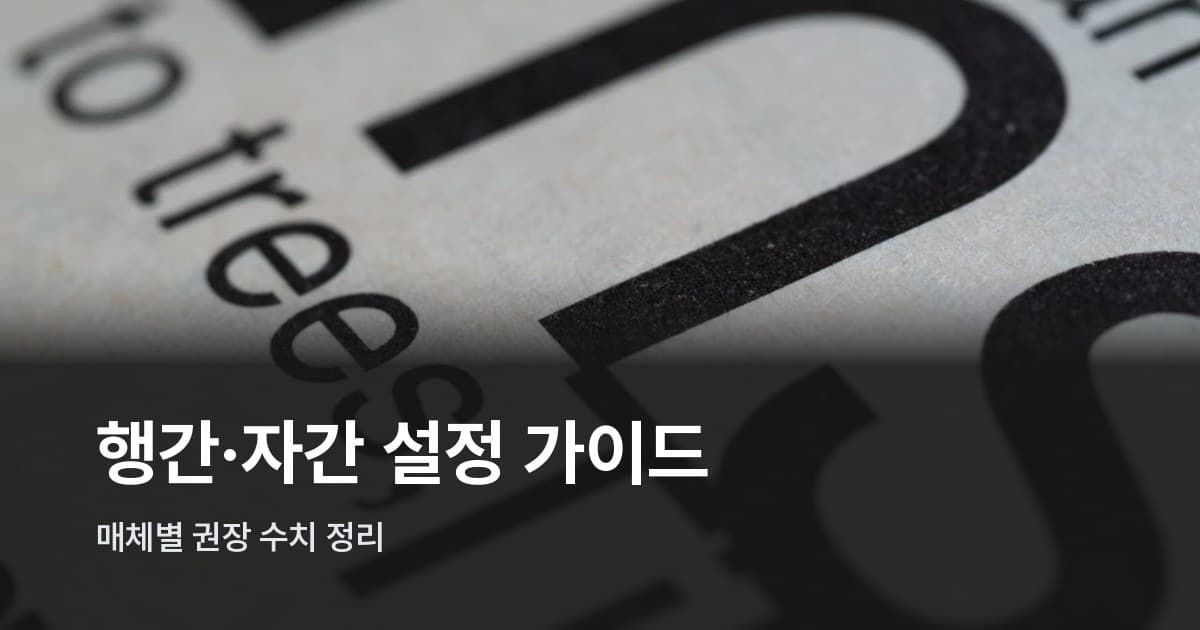
한글 폰트 행간·자간, 역할과 매체별로 수치가 다 다르다
흰 종이에 인쇄된 텍스트 클로즈업
line-height: 1.6을 나눔고딕에 적용했을 때와 Pretendard에 적용했을 때, 결과가 같은가? 눈으로 보면 다르다. 같은 수치를 줬는데 왜 다를까 — 그 질문이 이 글의 출발점이다.
행간과 자간 수치는 역할·매체만큼이나 폰트 자체의 구조에 영향을 받는다. 어느 폰트는 정사각형 틀을 꽉 채우고, 어느 폰트는 획이 가늘고 여백이 남는다. 이 밀도 차이가 동일 수치에서 완전히 다른 시각 밀도를 만든다. 수치 표를 보기 전에 이 원리를 이해하지 않으면, 표를 외워도 새 폰트로 바꿀 때마다 처음부터 다시 시작하게 된다.
폰트 구조가 같은 수치를 다르게 만든다
한글 서체는 대부분 초성·중성·종성이 고정된 정방형(正方形) 틀 안에 조합된다. 1980년대 디지털 조판이 표준화된 이후 이 구조가 굳어졌는데, 이 틀 안에서 획을 얼마나 크게 채우는지가 서체마다 다르다.
획이 틀을 빡빡하게 채우는 서체(나눔고딕, 본고딕 계열)는 글자 자체가 시각적으로 크게 보인다. 같은 font-size: 16px라도 텍스트 덩어리가 더 무겁게 느껴지고, 행간을 조금만 좁혀도 줄이 답답해 보인다. 나눔고딕으로 본문을 잡아두고 line-height: 1.6을 적용해 보면 "조금 빽빽하다"는 인상이 드는데, 1.7이나 1.75로 올리면 훨씬 숨통이 트인다. 긴 글을 읽을 때 특히 차이가 도드라진다.
반면 획이 가늘고 여백을 남기는 서체(Pretendard, Noto Sans KR)는 동일 크기에서 시각적으로 좀 더 작고 가볍게 느껴지며, 행간 1.6과 1.7의 차이가 상대적으로 덜 도드라진다. Pretendard로 블로그 본문을 짜면 1.6에서도 충분히 읽힌다는 느낌을 받는 경우가 많다. KoPub 바탕체 같은 명조 계열은 조금 달라서, 세리프 획의 특성상 행간을 1.7~1.8로 넉넉히 주지 않으면 획 끝부분이 서로 가까워 보여 뭉쳐 보이는 느낌이 난다.
자간도 마찬가지다. 정방형 틀의 모든 글자는 같은 폭을 갖는다 — 영문처럼 글자 쌍별로 커닝(kerning) 값이 다르게 들어가지 않는다. 이 균일한 고정 폭이 기본 상태에서 자간을 시각적으로 넓게 느끼게 만드는 원인이다. 그래서 한글에서 -0.01em 전후의 음수 자간이 관행처럼 쓰인다. 영문 본문에서 자간을 음수로 조정하는 일이 드문 것과 대조적이다.
폰트를 바꿀 때마다 행간·자간을 재확인해야 한다는 게 규칙이지 예외가 아니다. 같은 line-height: 1.6을 줘도 나눔고딕은 답답하고 Pretendard는 여유 있어 보인다면, 수치가 틀린 게 아니라 폰트의 획 밀도가 다른 거다.
한글 자간이 음수여야 하는 구조적 이유
영문 알파벳은 글자마다 폭이 다르고, 폰트 제작 단계에서 글자 쌍별로 커닝 값이 세밀하게 설정된다. 대문자 'AV' 사이를 당기고 'II' 사이는 그대로 두는 식이다. 한글은 이 커닝이 없다. 정방형 구조상 모든 글자가 같은 폭이고, 자간이 글자 오른쪽 끝에 균일하게 붙는다.
letter-spacing: 0을 그대로 두면 글자 사이 여백이 다소 넓어 보이는 경향이 생긴다. -0.01em 정도로 좁히면 시각적으로 더 자연스럽게 밀착된다. 이 차이는 특히 굵은 폰트 웨이트(Bold, ExtraBold)에서 더 잘 드러난다. 굵은 글자는 획 면적 자체가 넓어지기 때문에, 글자 간 여백이 상대적으로 더 넓어 보이는 효과가 생겨서 -0.01em이 아니라 -0.02em이 더 자연스럽게 맞아 들어가는 경우도 있다.
단, 아주 작은 크기(12px 이하)에서 음수 자간을 유지하면 획이 붙어 보이는 역효과가 나니, 캡션·레이블에서는 자간을 0 또는 약간 양수로 되돌린다.
WCAG 1.4.12는 사용자가 자간을 0.12em 이상으로 늘렸을 때도 레이아웃이 깨지지 않아야 한다고 명시한다. 그래서 고정 px 단위보다 em 단위가 유지보수에 유리하다 — 사용자가 브라우저 폰트 크기를 키웠을 때 간격도 함께 스케일되기 때문이다.
WCAG 2.1 AA가 정한 하한선
W3C의 WCAG 2.1 SC 1.4.12(Text Spacing, Level AA)는 디자인 권장값이 아니다. 사용자가 이 수준으로 재정의해도 콘텐츠가 살아남아야 하는 하한선이다.
항목최솟값 (폰트 크기 기준)CSS 표기 예시
줄 간격 (line-height)폰트 크기의 1.5배 이상line-height: 1.5
단락 간격 (paragraph spacing)폰트 크기의 2배 이상margin-bottom: 2em
자간 (letter-spacing)폰트 크기의 0.12배 이상letter-spacing: 0.12em
어간 (word-spacing)폰트 크기의 0.16배 이상word-spacing: 0.16em
실제 디자인의 기본값은 이보다 크게 설정하는 게 일반적이다. 여기서 흔한 실수가 하나 있는데, 컨테이너에 고정 height를 지정하면 사용자가 간격을 늘렸을 때 텍스트가 잘려나간다. WCAG 준수 여부와 무관하게 유연한 레이아웃이 기본이다.
이 기준은 "이 수치면 충분하다"는 뜻이 아니라 "이 아래로 내려가면 접근성 위반"이라는 뜻이다. 디자인 목적의 권장값은 아래 표가 따로 제시한다.
텍스트 역할 × 매체별 권장 행간·자간 수치
아래 표는 WCAG 기준, 실무 디자인 관례, 편집 디자인 표준을 종합한 참고 권장값이다. 폰트마다 설계 비율이 달라 동일 수치에서도 시각적 결과가 다를 수 있으니, 출력 결과를 직접 보면서 미세 조정하는 게 원칙이다.
🖥 웹(CSS)
텍스트 역할일반 크기권장 line-height권장 letter-spacing비고
대제목(H1)32~48px1.1~1.25-0.02em ~ -0.03em큰 글자일수록 행간 좁혀야 밀착감
소제목(H2~H3)20~28px1.3~1.4-0.01em ~ -0.02em본문보다 약간 좁게
본문(Body)15~18px1.6~1.8-0.01em ~ 0emWCAG 최솟값 1.5 초과 권장
캡션·레이블12~14px1.4~1.60em ~ +0.02em작은 글자는 자간 여유 있게
모바일은 기준이 조금 달라진다. 손에 쥐고 보는 거리는 짧지만, 좁은 화면에서 행간이 너무 크면 스크롤 피로가 쌓인다. OS별 단위 차이(Android의 sp, iOS의 pt)도 체크해야 한다.
모바일(Android sp / iOS pt)
텍스트 역할일반 크기권장 line-height권장 letter-spacing비고
대제목24~32sp(pt)1.15~1.3-0.02em좁은 화면에서 행간이 너무 크면 스크롤 과다
소제목18~22sp(pt)1.3~1.5-0.01em
본문14~16sp(pt)1.5~1.7-0.01em ~ 0emAndroid 14+: dp 대신 sp로 line-height 지정 권장
캡션11~12sp(pt)1.4~1.60em ~ +0.02emiOS 최소 권장 11pt
인쇄는 또 다른 세계다. 화면과 달리 픽셀이 없고 단위도 pt 고정값으로 바뀐다. 행간을 배율 대신 pt 절대값으로 지정하는 경우가 많은 것도 이 때문이다.
인쇄(단위: pt)
텍스트 역할일반 크기권장 행간권장 자간비고
대제목20~36pt폰트 크기의 1.1~1.3배-50~-80 (한컴 ‰ 기준)좁은 행간이 위엄감을 준다
소제목12~18pt1.3~1.5배-30~-50
본문9.5~10.5pt16~21pt 또는 1.7~2.0배-20~-40행간을 pt 고정값으로 쓰는 경우가 많다
캡션·각주7~9pt1.4~1.6배-10~+10너무 좁으면 획이 붙어 보임
인쇄 자간 단위, CSS em으로 환산하면
인쇄 표의 자간 수치는 웹 개발자에게 낯설게 보일 수 있다. 한컴 한글과 인디자인의 자간 단위는 폰트 크기의 1/1000(퍼밀, ‰)으로 표시된다. -50이면 폰트 크기의 5%를 좁힌다는 뜻이다.
CSS em 단위로 환산하면 이렇게 대응된다: 인쇄 본문의 -20~-40 ‰는 CSS 기준 -0.02em ~ -0.04em 수준이고, 대제목의 -50~-80 ‰는 -0.05em ~ -0.08em에 해당한다. 위 표의 웹 대제목 권장값(-0.02em ~ -0.03em)보다 인쇄 대제목이 더 좁게 조여지는 셈인데, 인쇄물은 300dpi 이상 고해상도에서 30~40cm 거리로 읽히기 때문에 획이 붙어 보이는 역효과가 훨씬 덜하다.
관람 거리와 해상도가 단위와 권장 범위의 차이로 이어지는 구조다. 인쇄물(30~40cm, 300dpi+), 모바일(25~35cm, 고밀도 픽셀), 데스크톱 모니터(60~90cm, 72~150dpi) — 이 세 조건이 다르기 때문에 매체별 범위가 갈라진다.
웹과 인쇄를 모두 다루는 디자이너라면, 자간 단위 변환 감각을 익혀두는 게 실무에서 꽤 유용하다. 인디자인에서 -30으로 잡던 감각을 CSS에서는 -0.03em으로 그대로 옮길 수 있다는 걸 알면 매체 전환 작업이 한결 수월해진다.
실전 CSS 출발점
아래는 웹 한글 본문의 실용적인 시작 코드다. 이 값을 고정 답이 아닌 출발점으로 쓰고, 선택한 폰트의 획 밀도에 따라 ±0.05~0.1 범위 내에서 조정한다.
/* 기본 본문 — 획 밀도 중간 수준 폰트(Pretendard, Noto Sans KR) 기준 */
body {
font-size: 16px;
line-height: 1.7;        /* 한글 본문 기본값 */
letter-spacing: -0.01em; /* 한글 자간 약간 좁히기 */
}
h1, h2 {
line-height: 1.25;
letter-spacing: -0.02em;
}
figcaption, .caption {
font-size: 13px;
line-height: 1.5;
letter-spacing: 0;
}
폰트를 바꾼 뒤에는 CSS를 건드리기 전에 먼저 새 폰트의 획 밀도를 눈으로 확인한다. 글자가 틀을 빡빡하게 채우면 행간을 0.05~0.1 올리는 것부터 시작하고, 가볍고 여백이 많은 폰트라면 현재 값에서 유지하거나 약간 줄인다. 같은 수치인데 폰트만 바꿨더니 느낌이 확 달라지는 순간이 오면, 이 글이 왜 폰트 구조를 먼저 짚었는지 바로 이해가 될 거다.